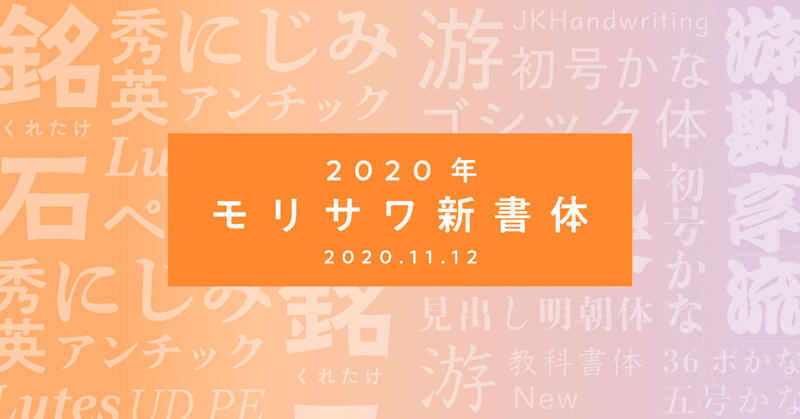
モリサワ新書体2020のご紹介〜見本帳の中身、見せちゃいます〜
2020年11月12日(木)に2020年度の新書体をリリースいたしました。
各書体の特徴について、新書体見本帳に掲載されているビジュアルを交えつつご紹介していきますので最後までお見逃しなく!
1.ラインナップ紹介
本年度リリースするのは、こちらの4書体です。
左上から、フェルトペンのメモ書きのような親しみやすい印象のペン字体「ぺんぱる」、 中国晋代の碑文と日本の近代活字を復刻した柔らかなゴシック体「くれたけ銘石」、 漫画の吹き出しや辞書の見出しなどで使用されるアンチック体にインクのにじみ加工を施した 「秀英にじみアンチック」、ローコントラストでありながらもクリアですっきりとした印象のセリフ書体 「Lutes UD PE」です。
また、今回の新書体追加に合わせて「黎ミン」「新ゴ」「新丸ゴ」のAP版のほか、 かな書体「秀英アンチック」と「秀英角ゴシック」の漢字を組み合わせた「秀英アンチック+」も追加されます。
...概要をご説明しましたが、文字で文字の説明をするのは難しいですね。
百聞は一見にしかず!ということで、ここからは新書体見本帳2020のビジュアルをお見せしながら、各書体の特徴と関連情報をご紹介します。
2.ぺんぱる
「ぺんぱる」は、フェルトペンでラフに手書きしたような、親しみやすい雰囲気を持つデザイン書体です。
ひらがなの“ま”や漢字の“東”の横線がつながっているなど、フリーハンドならではのユニークな筆の運びやスピード感が特徴です。
手書き風ではありますが、ただ書いた文字をスキャンするだけではなく、一文字ずつアウトラインを確認しながら作成しています。字面や文字位置の丁寧な調整・部首統一も行っているので、統一感と読みやすさを兼ね備えた書体になっています。
ご覧のようなメニュー表や食品パッケージ、見出しやキャプションなどで柔らかい印象を与えます。(おいしそう…)
・書体名の由来
「ぺんぱる」は、文通仲間を意味する"ペンパル"に、手紙のような優しい思いを込めた雰囲気で使ってもらいたい、という意味を込めて名づけました。
実はこの書体のデザインは、子どもの連絡帳にお母さんが書くような文字をイメージして作られました。そのため、ペンと紙のような物質感を連想させるような名前にしたいと考え、候補を絞っていきました。
また、“は”や“ほ”などの、書体の中で特徴的なデザインのかなを名前にも使いたいと考えていました。
これらを総合的にみて生まれたのが「ぺんぱる」という名前です。
手書きの風合いが持つ優しさや親しみやすさを感じていただけたなら嬉しいです。
手書き風の書体といえば、2017年に「黒曜」、2019年に「小琴京かな」「小琴遊かな」「剣閃」をリリースするなど、実はモリサワでは手書きのニュアンスを持つ書体のバリエーションが少しずつ増えています。
3.くれたけ銘石
「くれたけ銘石」は、中国南京市郊外で出土した晋代の墓誌銘『王興之墓誌』より復刻した漢字書体「銘石(めいせき)」と、 森川龍文堂の活字見本帖『活版総覧』から復刻した和字書体「くれたけ」を組み合わせた オールドスタイルのゴシック体です。
和字書体:ひらがなとカタカナのみの書体
漢字書体:漢字のみの書体
見本帳では、俳句で組んでみました。隷書体をベースに彫刻の味わいが加わった書風から、 どこか懐かしい素朴な魅力を感じますよね。
実はこの「くれたけ銘石」 、今までにモリサワから出されているフォントの中に仲間がいます。 それがこちら。
これらは全て、同じタイプファウンダリーから提供いただいている書体です。「きざはし金陵」「かもめ龍爪」「さくらぎ蛍雪」が既にリリースされており、 今回「くれたけ銘石」が加わります。
モリサワからリリースするにあたっては、文字セットの拡張やペアカーニングの追加などの細かな品質調整を行っており、個性的な書体を最新の仕様でご利用いただけます。
ちなみに、これらの書体名にはルールがありまして、和字書体と漢字書体の名前の組み合わせでできているんです!「くれたけ銘石」であれば、「くれたけ」という和字書体と「銘石」という漢字書体が組み合わせてある、ということになります。
“和字(かな)”と“漢字”、別々にフォーカスしてみるのも、書体の楽しみ方のひとつですね。
4.秀英にじみアンチック
「秀英にじみアンチック」は、漫画の吹き出しや辞書の見出しなどで使用される書体「秀英アンチック」をベースに、活版印刷による紙面上でのインクのにじみを再現した書体です。
元になっている「秀英アンチック」はもともとかなと一部の記号類のみが搭載された“かな書体”として提供されており、「秀英角ゴシック」の漢字を組み合わせることが推奨されていました。こういった、書体を組み合わせて使うことを“混植”といいますが、アンチック体のかなとゴシック体漢字の混植は、通称“アンチゴチ”とよばれています。
いままで混植をするには組版をするアプリケーション上での設定をしなければなりませんでした。しかし「秀英にじみアンチック」と、今回合わせてリリースする「秀英アンチック+」は、最初から「秀英にじみ角ゴシック」「秀英角ゴシック」の漢字が組み合わせてあるので、かなと漢字をそのまま打ち出すことができます。
にじみのある「秀英にじみアンチック」を、にじみのない「秀英アンチック+」と比べてみると、こんな感じです。大振りで重厚な明朝デザインのかななので、にじみがなくても存在感がありますが、線の揺らぎや交差部分のにじみ加工が加わることで、より深みのある雰囲気になっていると思いませんか?
秀英体にじみシリーズも年々数が増えてきました。
既存の書体と合わせて、幅広いシーンで使っていただければと思います。
5.Lutes UD PE
「Lutes UD PE」はデジタルデバイス上での視認性に配慮するため、ローコントラストでありながらもクリアですっきりとした印象のデザインに仕上げています。 ローコントラストというのは“線の太さの差が少ない”という意味です。
豊富な言語サポートを展開していますので、近年需要が高まりつつある既存コンテンツの多言語化、デジタル化などのご利用に最適です。
書体名についている“PE”が気になった方!さすがです。
“PE”(汎ヨーロッパ)というのは、モリサワが定めた欧文書体の独自セットの名称です。ラテンアルファベットに加えて、キリル文字、ギリシャ文字、およびベトナム語用文字をカバーしていて、151言語に対応しています。
既存の和文書体などと組み合わせていただくことで、より広い言語をサポートした表記に対応が可能です。